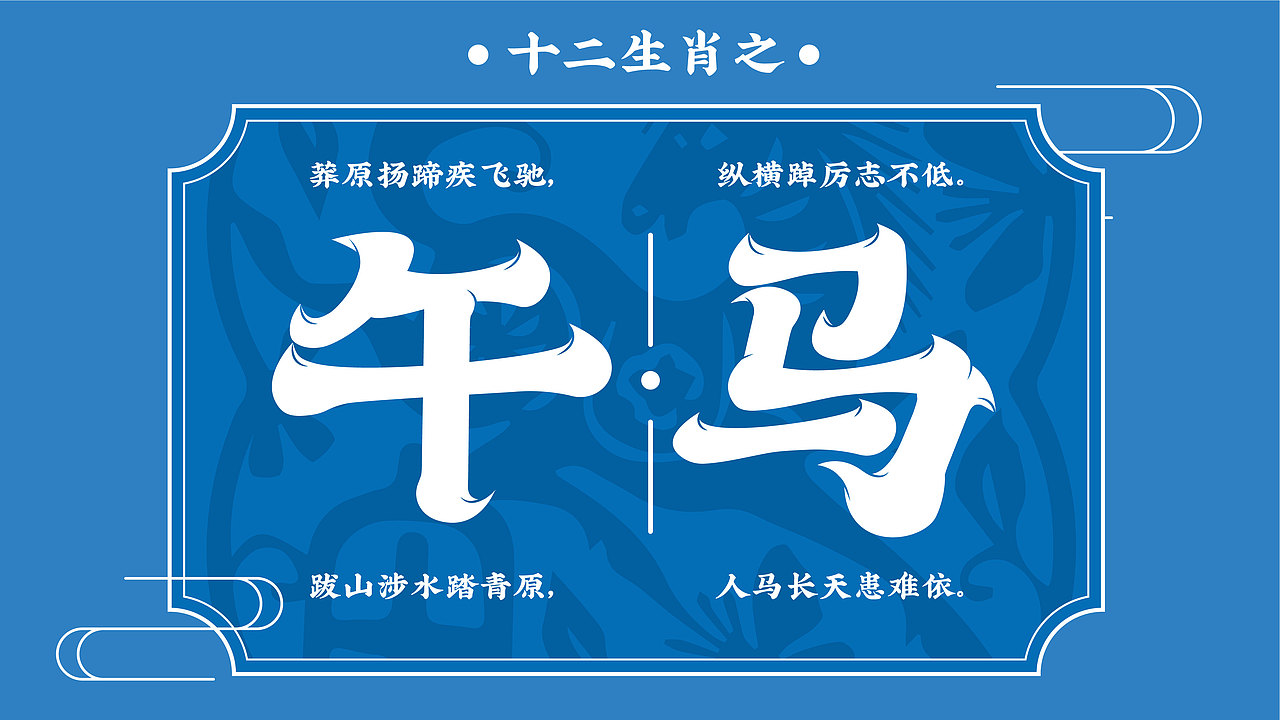
十二生肖系列字体设计
这是以十二生肖为主题设计的一套字体。
十二生肖,又叫属相,是十二地支的形象化代表,即子(鼠)、丑(牛)、寅(虎)、卯(兔)、辰(龙)、巳(蛇)、午(马)、未(羊)、申(猴)、酉(鸡)、戌(狗)、亥(猪),随着历史的发展逐渐融合到相生相克的民间信仰观念,反映在婚姻、人生、年运等,每一种生肖都有丰富的传说,并以此形成一种观念阐释系统,成为民间文化中的形象哲学,如婚配上的属相、庙会祈祷、本命年等。现代,更多人把生肖作为春节的吉祥物,成为娱乐文化活动的象征。
在此套字体中将笔画张力大的髭文字风格与传统生肖全称相结合,并且加入了十二生肖诗,是当代诗人贵谷子先生所创作,它通俗幽默,妙趣横生,令人捧腹。二者将结合保证了字体风格整体性的同时也契合了现代年轻人清新欢快的调性。背景融入对应生肖的剪纸图案,是传统与现代的一次有机结合。